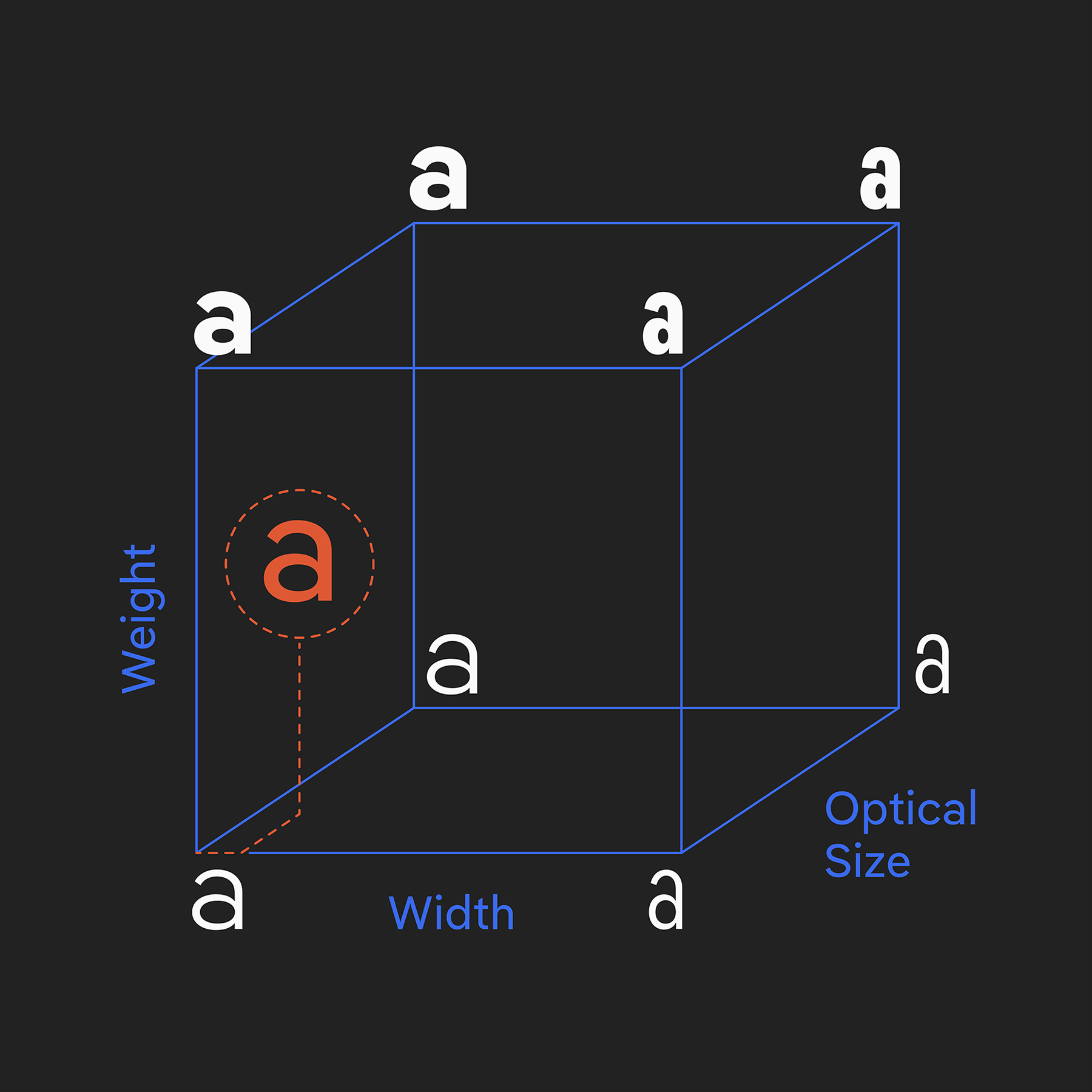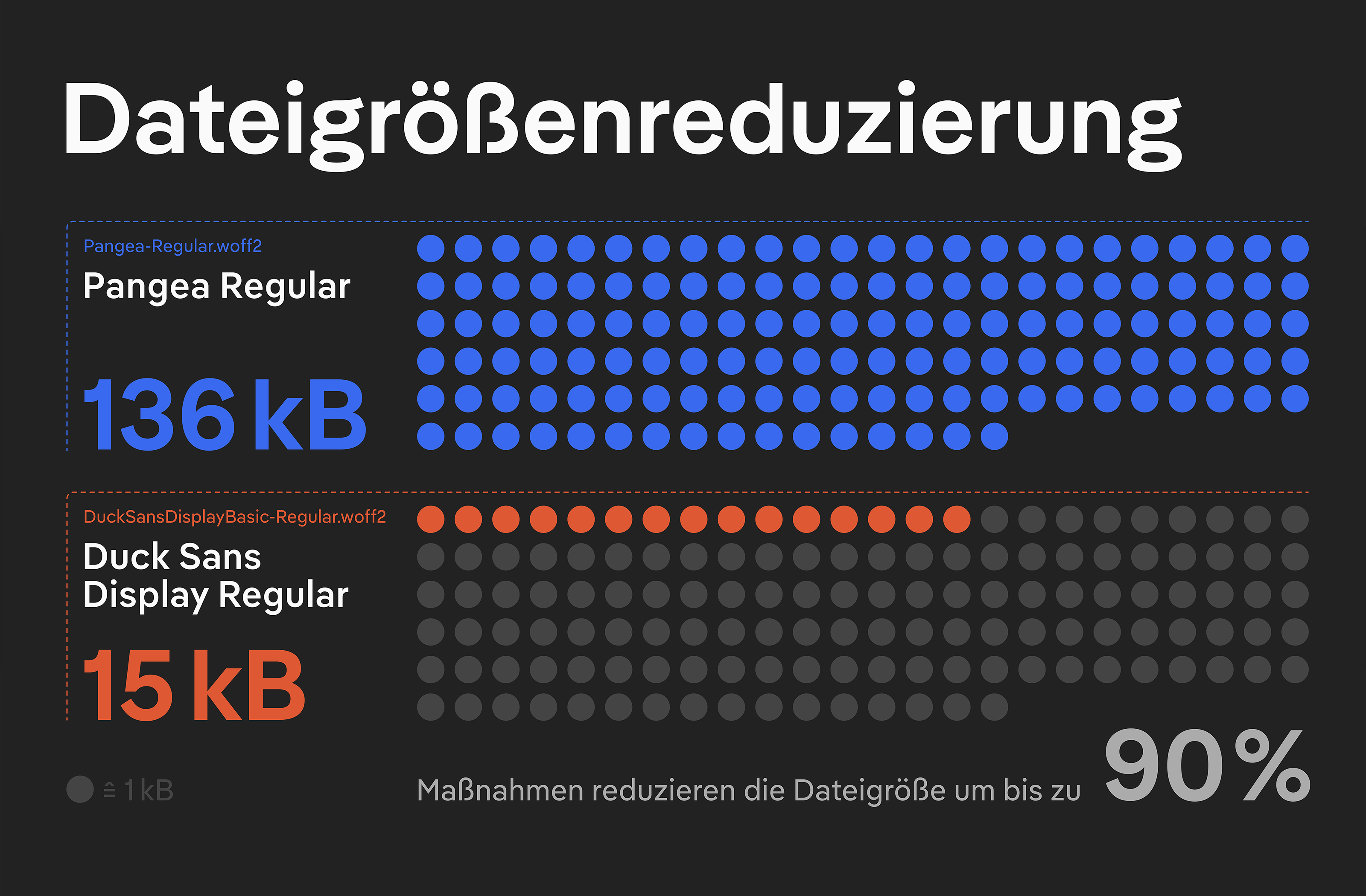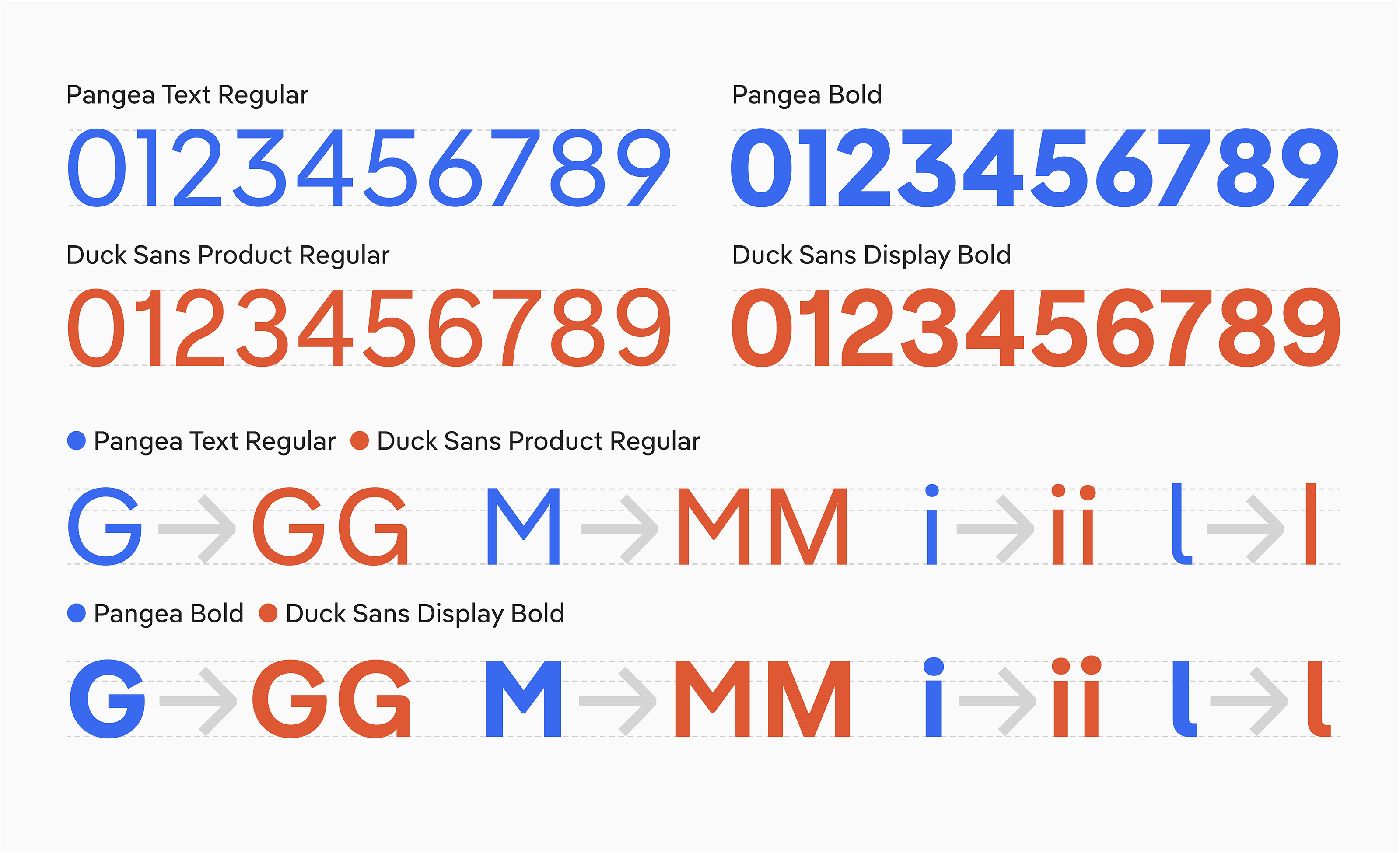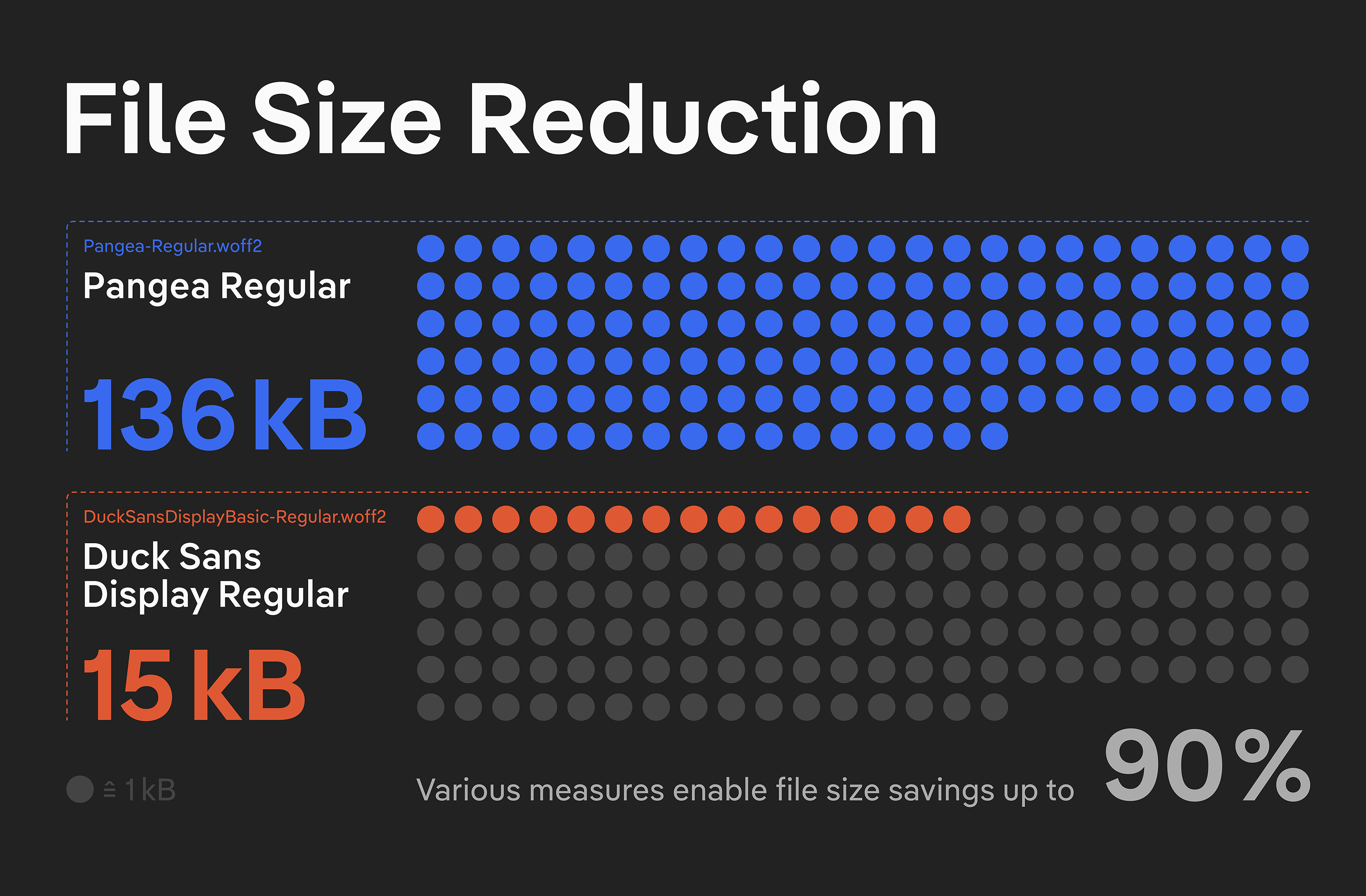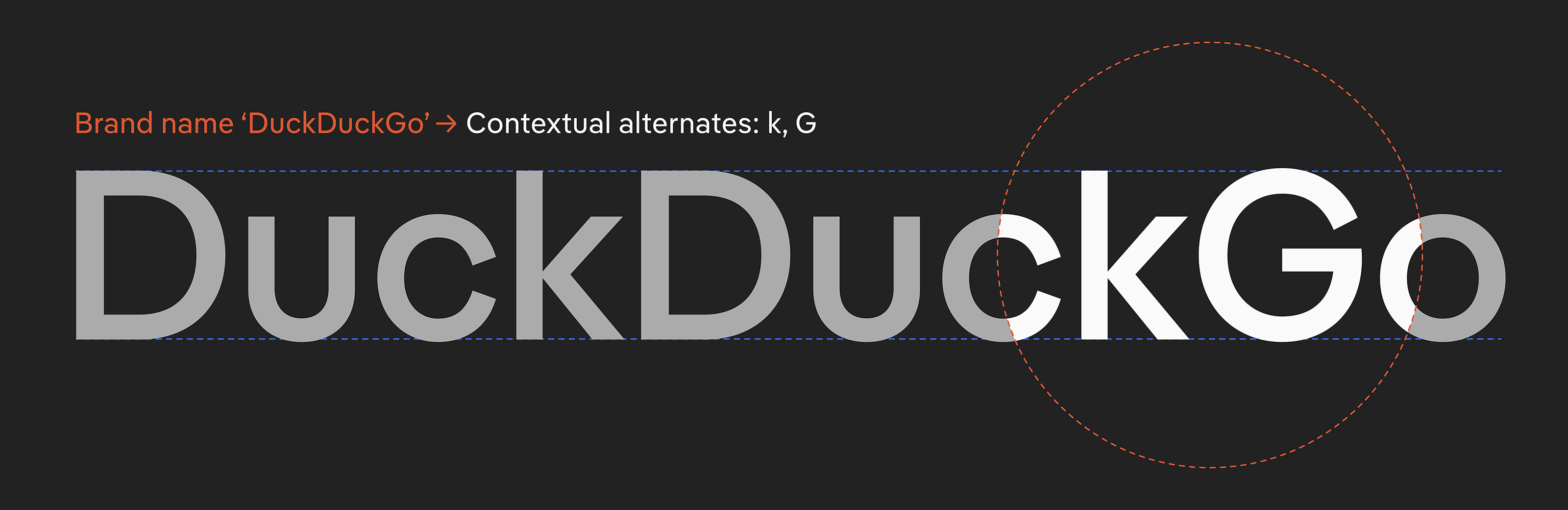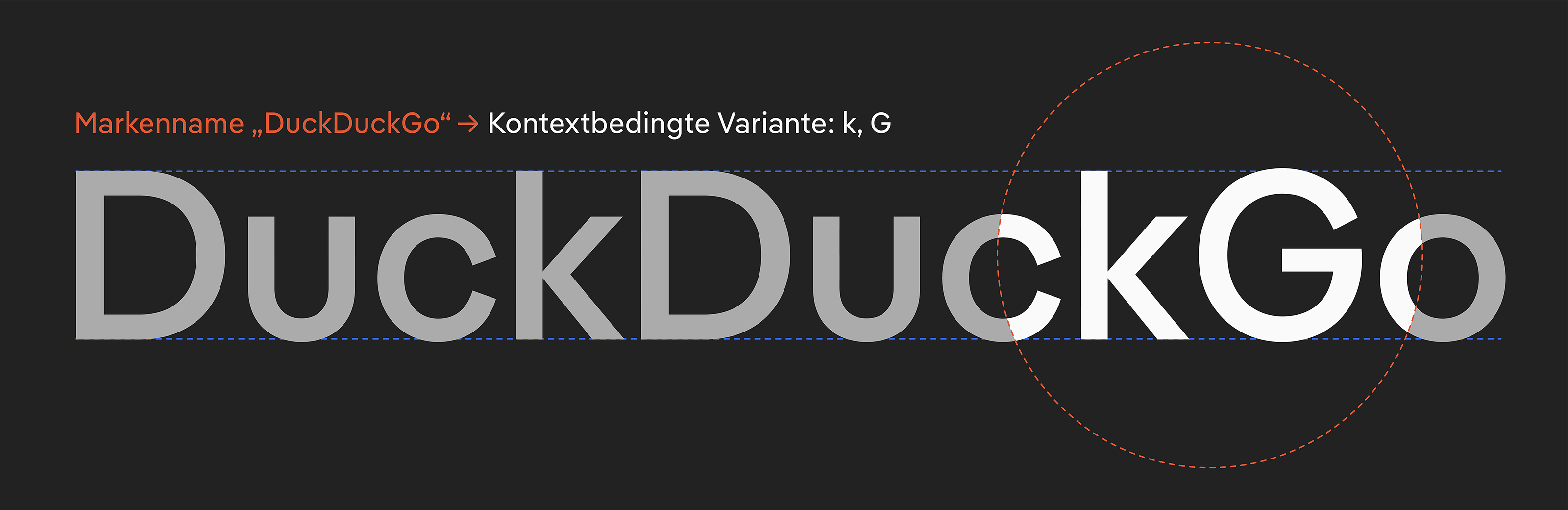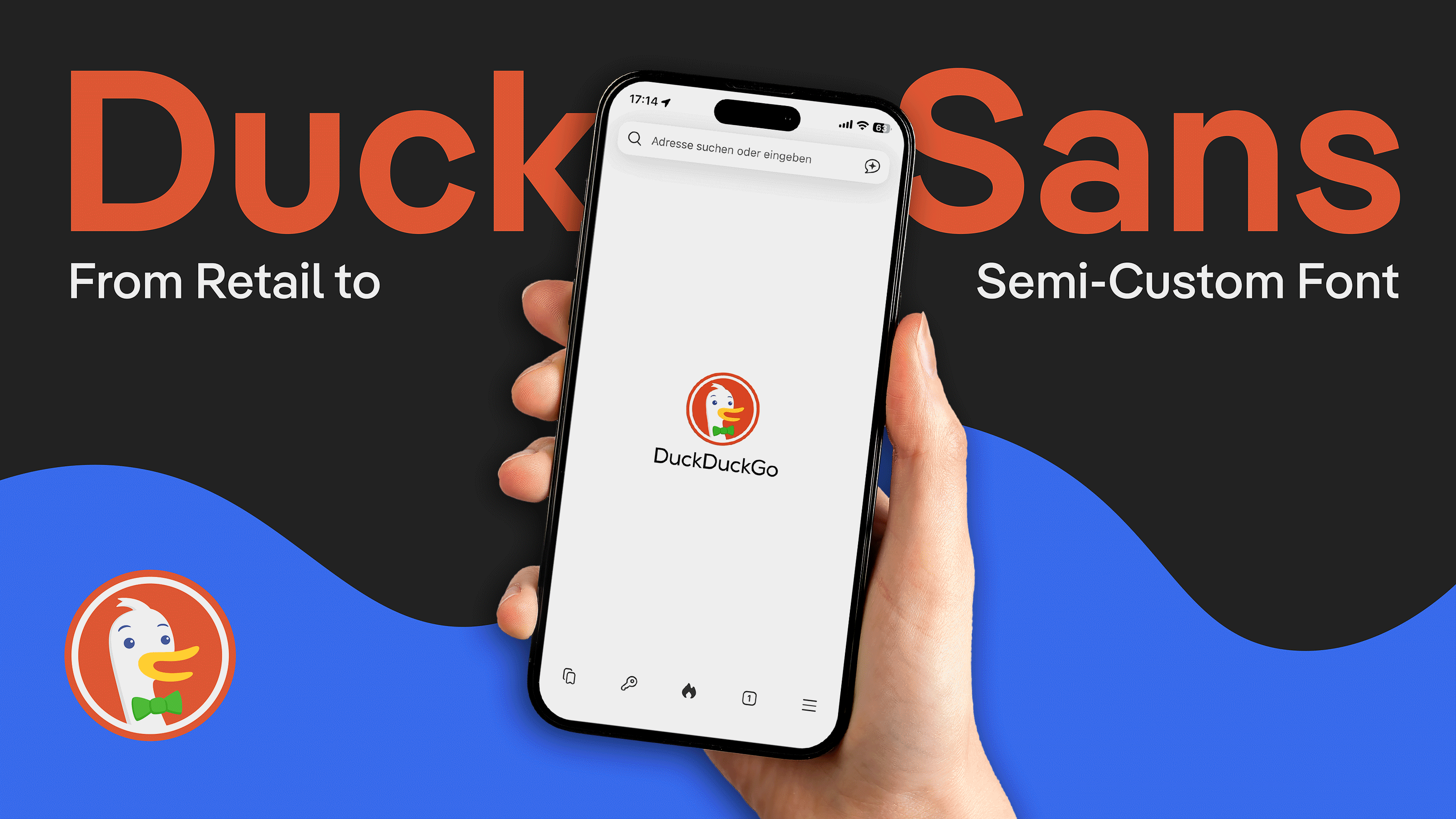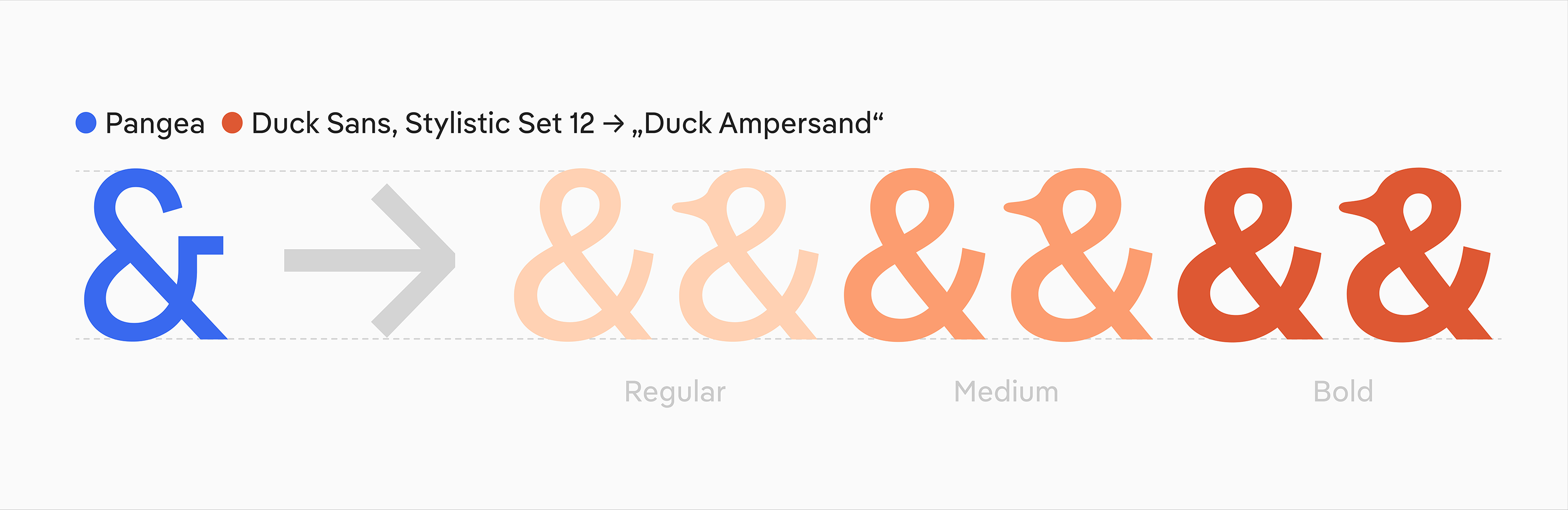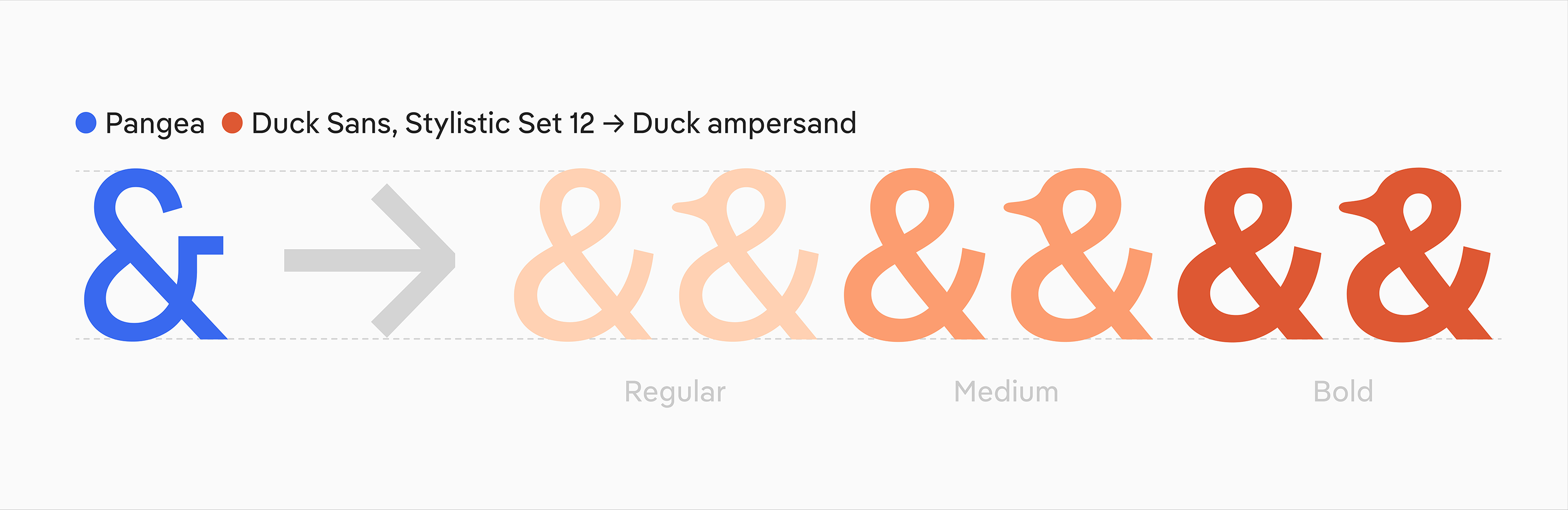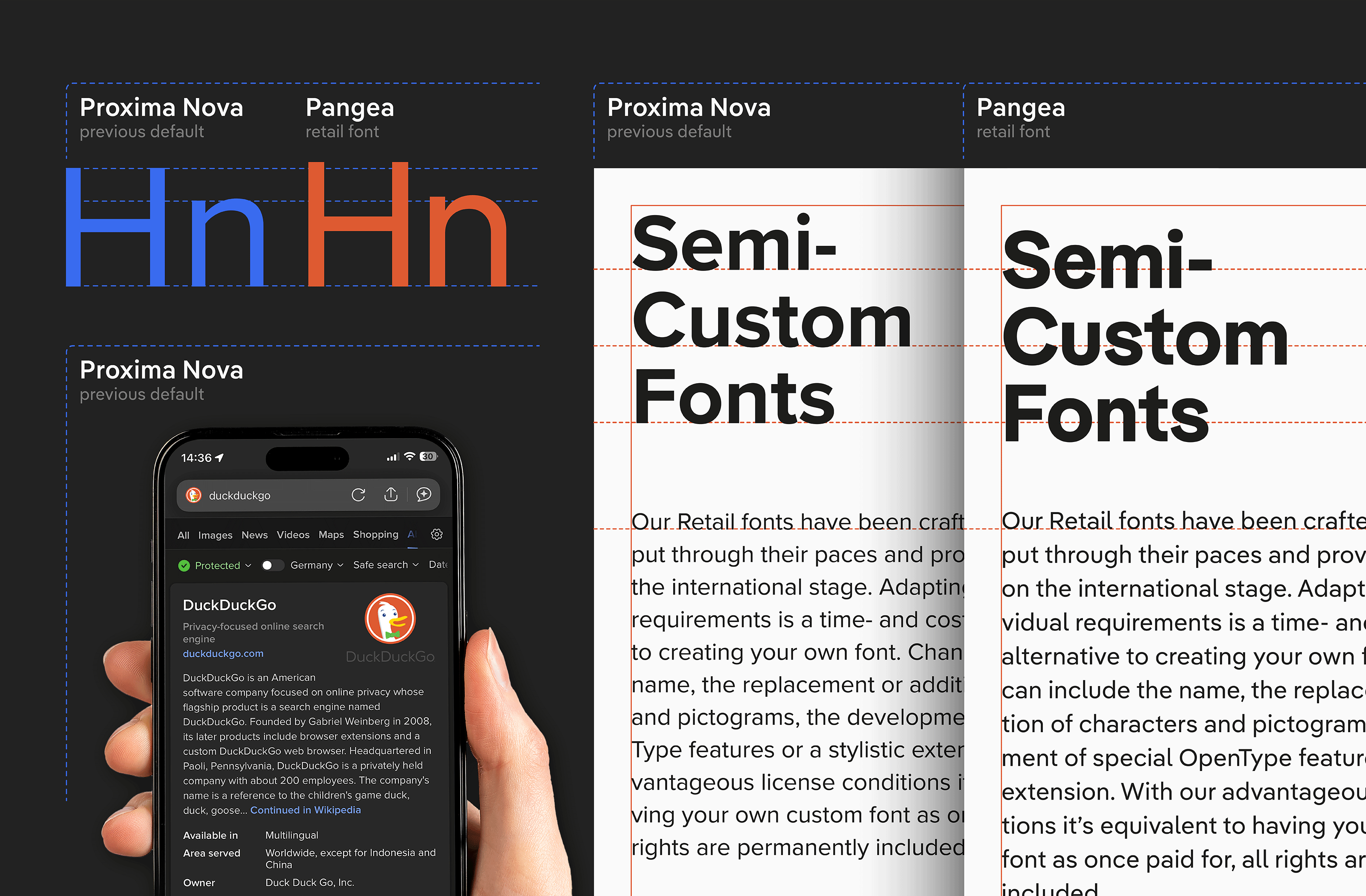
Aus Pangea wird Duck Sans
Semi-Custom-Font für DuckDuckGo: Aus Pangea wird Duck Sans
Bei Fontwerk haben wir das Glück, mit spannenden Unternehmen unterschiedlichster Branchen zusammenarbeiten zu dürfen. Es kommt aber nicht alle Tage vor, dass eine Anfrage einer echten Love-Brand hereinflattert.
S
o geschehen im Frühjahr 2025, als das US-Internetunternehmen DuckDuckGo auf der Suche nach einer unverwechselbaren, die Marke repräsentierenden Schriftart Interesse an einer angepassten Pangea äußerte, um sie als Default-Font in ihrer gleichnamigen Suchmaschine einzusetzen.
Die Begeisterung bei Pangeas Designer Christoph Koeberlin und Verleger Ivo Gabrowitsch war groß, denn beide schätzen seit Jahren den USP von DuckDuckGo – im Gegensatz zu bekannteren Suchmaschinen sammelt sie keine persönlichen Informationen über ihre Nutzerinnen und Nutzer und spielt für alle die gleichen Ergebnisse aus.
Zunächst sollte die originale Pangea an einem kleinen Teil ihrer User getestet werden, um zu beobachten, ob und wie dadurch deren Verhalten beeinflusst werden würde. Der Test wurde bereits nach 24 Stunden als Erfolg gewertet. Fortan konnte die Schrift in den Einstellungen als Alternative zum bisherigen Default-Font Proxima Nova gewählt werden.
Parallel begann die Arbeit an den gewünschten Modifizierungen. Um aus der Pangea den Semi-Custom-Font ‚Duck Sans‘ zu machen, arbeitete Fontwerk eng mit dem DuckDuckGo-Brand-Team zusammen. Zur Vermeidung allzu großer Sprünge in den Seh- und Lesegewohnheiten der Anwenderinnen und Anwender musste dazu die Größe der Schrift an die bisherige angepasst werden. Das bedeutete eine rund 3%-ige Verkleinerung aller Glyphen mit entsprechender Anpassung der vertikalen Metriken und Positionierungen von Akzenten.
Das Team von Fontwerk arbeitet an der einzigartigen Schnittstelle zwischen Kunst, Design und vor allem Technik – eine Kombination, die nur selten zu finden ist.
Semi-Custom-Font für DuckDuckGo: Aus Pangea wird Duck Sans (Vorher-Nachher-Vergleich)
Pangeas Schriftgröße musste an die bisherige angepasst werden (Proxima Nova). Das bedeutete eine rund 3%-ige Verkleinerung aller Glyphen mit entsprechender Anpassung der vertikalen Metriken und Positionierungen von Akzenten.
Semi-Custom Font for DuckDuckGo: Pangea transforms into Duck Sans (Samples)
Beabsichtigt waren zudem Anpassungen an weiteren Zeichen wie dem ‚G‘ (eigenständiger), dem ‚&‘ (geschlossen) und den i-Punkten (kräftiger) sowie neu zu zeichnende Ziffern, die ‚groteskiger‘ werden sollten. Außerdem sollte die stilistische Alternative des Minuskel-l (ohne Fuß) in der Text-Version zum Standard werden, die drei Schnitte Regular, Medium und Bold jeweils etwas dünner werden und ggf. die Laufweite der Display-Variante etwas reduziert werden. Diese Anforderungen ergaben sich nach internen Tests mit den variablen Fonts.
Semi-Custom-Font für DuckDuckGo: Aus Pangea wird Duck Sans (Designspace)
Auch dafür eignen sich Variable-Fonts: Das DuckDuckGo-Brand-Team testete, welche konkreten Strichstärken, Breiten und Parameter für optische Größen sich am besten eignen. Auf Grundlage dieser Tests wurden die statischen Fonts produziert.
Semi-Custom Font for DuckDuckGo: Pangea transforms into Duck Sans (Semi-custom modifications)
Gewünscht waren zudem Anpassungen an weiteren Zeichen wie dem ‚G‘ (eigenständiger), dem ‚M‘ und den i-Punkten (kräftiger). Die Ziffern wurden neu gezeichnet, sie sollten ‚groteskiger‘ werden.
Semi-Custom-Font für DuckDuckGo: Aus Pangea wird Duck Sans (Alternative Ampersands)
Das Standard-‚&‘ wurde geschlossen und um ein alternatives ‚Duck Ampersand’ für plakative Zwecke ergänzt.
In Rahmen weniger Feedbackrunden wurden diese stilistischen Änderungen durchgeführt, wobei einige davon lediglich Einzug in Stylistic-Alternates hielten (erreichbar via OpenType). Im Laufe der Zusammenarbeit ergaben sich weitere Wünsche der Individualisierung – so gibt es in den Stylistic Sets nun zusätzlich noch ein alternatives ‚M‘ sowie ein drittes ‚Duck Ampersand‘ für plakative Zwecke; das besondere ‚G‘ und ein daran angepasstes ‚k’ findet automatisiert im Kontext der Nennung des Markennamens ‚DuckDuckGo‘ Verwendung. In kurzer Zeit wurde aus der Pangea die ‚Duck Sans Display‘ für Überschriften und aus der Pangea Text die ‚Duck Sans Product‘ für den Großteil der Anwendungszwecke.
Semi-Custom-Font für DuckDuckGo: Aus Pangea wird Duck Sans (Kontextbedingte Alternativen)
Dank OpenType-Magie finden ein besonderes ‚G‘ und ein daran angepasstes ‚k’ automatisiert im Kontext der Nennung des Markennamens Verwendung.
Fontwerk hat ein feines Gespür dafür, was es bedeutet, Schriften für moderne, skalierbare Produkte mit unzähligen Anwendungsfällen in einer Vielzahl von Medien zu entwerfen. Von Nischen-Browser-Spezifikationen bis hin zu großflächigen Reklameflächen.
Eine weitere Herausforderung bestand im Wunsch, die Dateigrößen bestmöglich zu reduzieren. Hintergrund: bei 100 Millionen Suchanfragen täglich summiert sich jedes Kilobyte Daten auf mehrere Gigabyte, die Auswirkungen auf die Ladegeschwindigkeit und den CO2-Fußabdruck haben. Um hier einen möglichst großen Impact zu erzielen, wurden die Fonts in verschiedene Sprachräume aufgeteilt. Drei Haupt-Subsets bauen aufeinander auf: ‚Basic Latin‘ für die weltweit am meisten gesprochenen lateinischen Sprachen, ‚Complete Latin‘ für alle weiteren lateinischen Sprachen (Besonderheit der Pangea: sie beherrscht sämtliche Sprachen des lateinischen Alphabets!) und Kyrillisch/Griechisch. Zudem wurden Zeichen, die für alle Sprachräume relevant sind – etwa Währungszeichen, Brüche und Symbole – in eine separate Datei gepackt (‚Supplement‘). So können die Ladezeiten je nach Browser-Sprache des Nutzers oder der Nutzerin über CSS-Font-Stack effizient gesteuert werden.
Zu guter Letzt machte sich hier das manuelle Hinting (eine technische Möglichkeit der Bildschirmoptimierung, insbesondere für ältere Windows-Systeme) bezahlt, welches im Vergleich zum branchenüblichen Autohinting nicht nur bessere Ergebnisse erzielt, sondern sparsamer in Bezug auf die Dateigröße ist. Ein Beispiel: Die Datei DuckSansDisplayBasic-Regular.woff2 lässt sich mit der Gesamtheit dieser Maßnahmen um bis zu 90% reduzieren (nicht-gesubsettete Version der regulären Retail-Pangea 136kB vs. Basic-Variante der DuckSans 15kB). Im Vergleich zur vorherigen Hausschrift ist die Dateigrößen-Ersparnis sogar noch gravierender.
Semi-Custom-Font für DuckDuckGo: Aus Pangea wird Duck Sans (Dateigrößenreduzierung)
Eine zentrale Aufgabe bestand zudem in der Reduzierung der Dateigrößen.
Die Zusammenarbeit mit leidenschaftlichen Type-Nerds, die ihre Arbeit wirklich lieben, hat die gesamte Kooperation umso angenehmer gemacht.
Die ‚Duck Sans‘ ist ein exzellentes Beispiel, wie effizient eine perfekt passende Hausschrift kreiert werden kann. Wir nennen den Weg, eine bestehende Retail-Schrift auf individuelle Wünsche hin anzupassen ‚Semi-Custom-Fonts‘ und empfehlen sie häufig Kundinnen und Kunden, die mit dem Wunsch eines neu zu zeichnenden Custom-Fonts an uns treten nach eingehender Analyse des Bedarfs als geeignetere, weil zeit- und kosteneffiziente Alternative.
Die konkreten Vorteile sind beeindruckend, der wichtigste: Lizenzen für Semi-Custom-Fonts sind in den allermeisten Fällen deutlich günstiger als Custom-Fonts.
Man kann zudem aus einer riesigen Auswahl gut ausgebauter und umfänglich geprüfter Schriften wählen, die von den Kunden für einen eigenen ersten Eindruck im Produkt oder Branding getestet werden können.
Modifizierungen sind in jeglicher Art und Weise auf individuelle Bedürfnisse hin möglich und, je nach Umfang, innerhalb weniger Tage oder Wochen verfügbar. In Kombination mit fairen und weitreichenden Lizenzvereinbarungen werden Semi-Custom-Fonts somit selbst zu Exklusivschriften.